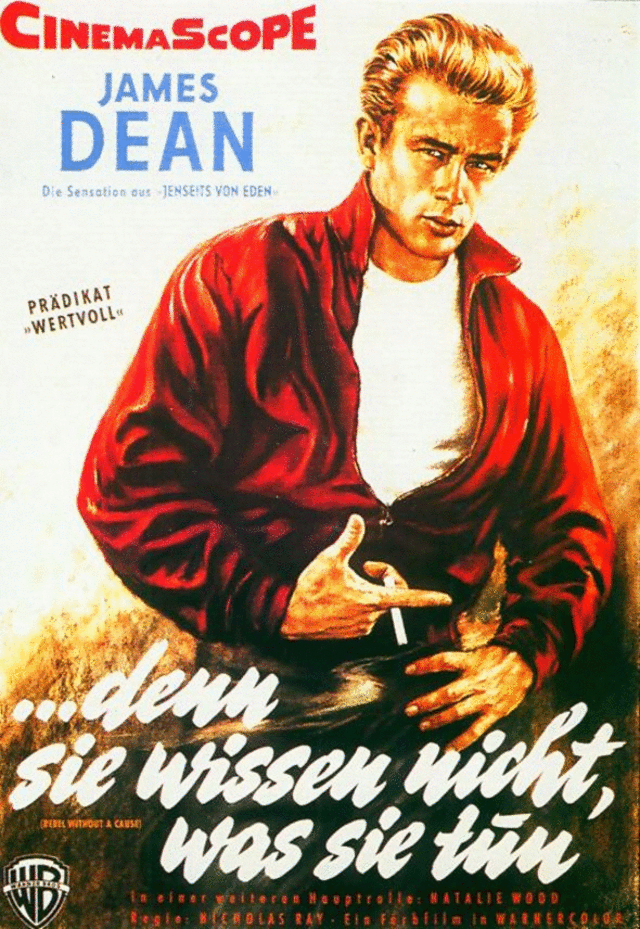
Schrift von Filmplakat "Denn sie wissen nicht was sie tun" gesucht
"… denn sie wissen nicht, was sie tun": Handgeschrieben oder ein Font? Nur welcher?
Auf dem Originalplakat bestimmt von Hand (jedes s ist ja anders) ... wir suchen also was möglichst Ähnliches?!
Handgeschrieben? Mir scheinen alle Ns unterschiedlich zu sein. (Die Esse haben mich erst ein bisschen verwirrt, weil 4 von 5 sehr ähnlich aussehen – fast so, dass ich dachte, das könnte nicht handgeschrieben sein – mit einem sehr charakteristischen Hacker links unten. Aber auch da fällt das zweite S aus dem Rahmen.)
4 von 5 sehr ähnlich aussehen
(Die Neigungswinkel in den oberen "Öffnungen" sind jeweils anders. Bei richtig guten Schriftenmalern sind die Ansätze fast immer identisch, darum schau ich eher auf die Negativformen.)
Die e und n sind wohl auch alle unterschiedlich, das Plakat wurde also zumindest handwerklich von Hand gemacht. Gibt’s aber eine Satzschrift, die der sehr ähnlich ist oder gar zugrundeliegt?
Wenn es heute eine digitale Satzschrift gibt, die diesen Texten auf dem Plaket, und wohl auch im Vor- und Nachspann des Films, die damals auch sehr sehr oft handgeschrieben waren entspricht, wird es mit dem Zugrundeliegen wohl eher umgekehrt sein.
Die Film-Kalligraphen waren damals derart in Übung, das sie ohne eine Vorlage zu benötigen viele hundert Namen im Nachspann frei aber fast wie gedruckt schreiben konnten .
Die ist auch zu aufrecht, ne:-?
Die ist auch schön, aber so spitz ;-)
... vielleicht muss man die neu zeichnen?! :hammer: Wofür brauchst du sie denn?
(sind ja nur 11 Buchstaben ;-) )
Ich frag für einen Bekannten … wenn es sie denn aber gäbe, würde sie mir durchaus auch gefallen. Als kompletter Font, natürlich. ;-)